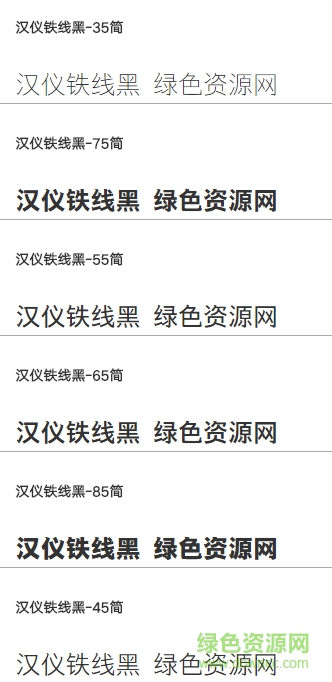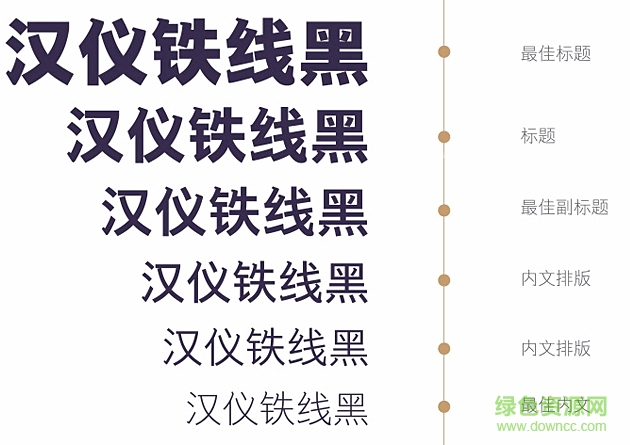
漢儀鐵線黑是一款筆畫流暢的漢儀字體,精簡而不失活力、輕柔而不失剛硬,廣泛被廣告設計、海報創(chuàng)意人士選用,綠色資源網(wǎng)為大家?guī)砹顫h儀鐵線黑字體,歡迎免費下載使用!
漢儀鐵線黑字體介紹
漢儀鐵線黑包括漢儀鐵線黑55簡、85簡、65簡等六款。
漢儀鐵線黑靈感來源于唐代李陽冰的鐵線篆書,其書風脫于玉筋書,因其結構圓熟優(yōu)美,筆畫纖細如線,剛勁似鐵而得名。
漢儀鐵線黑55簡
漢儀鐵線黑是一款溫暖有手寫意味的黑體,將書法的運筆特點融入現(xiàn)代黑體中,彰顯中華文明的藝術字體韻味。